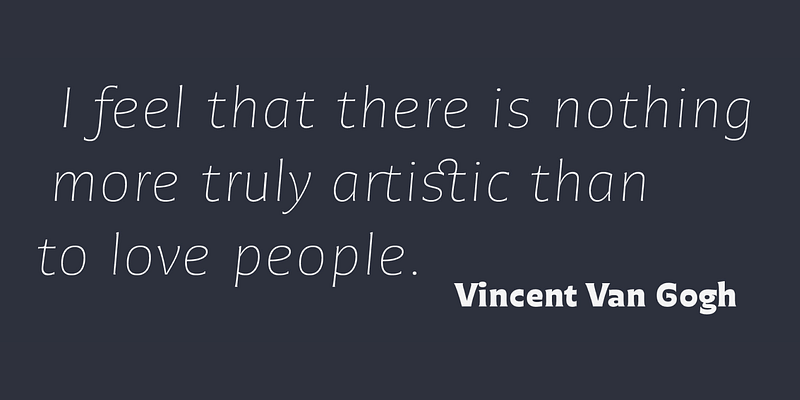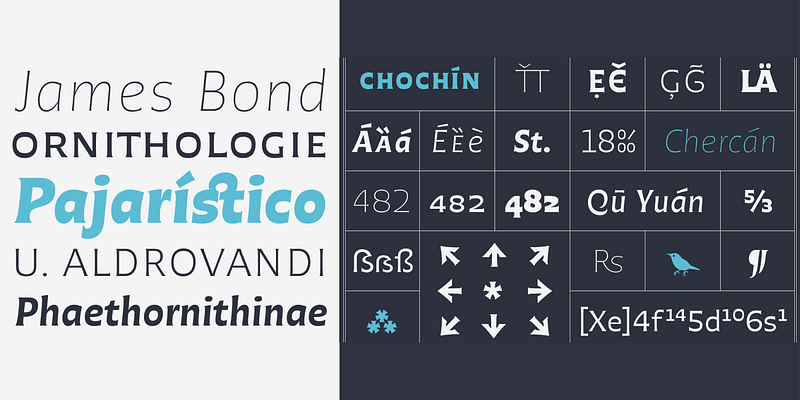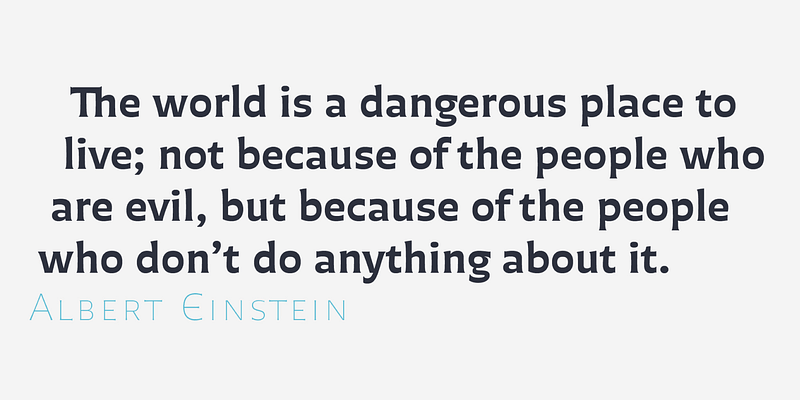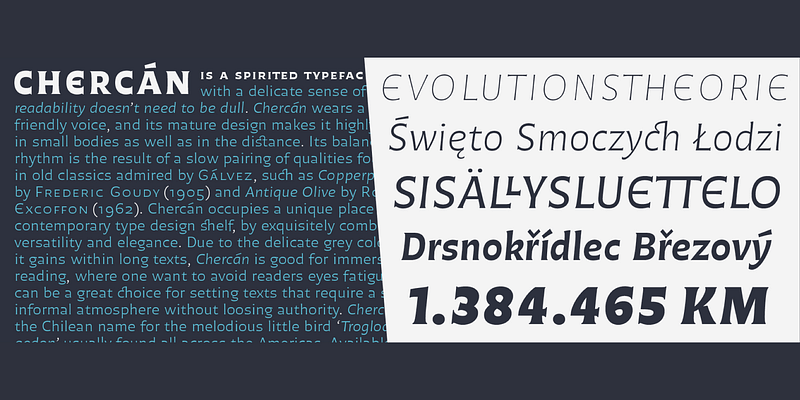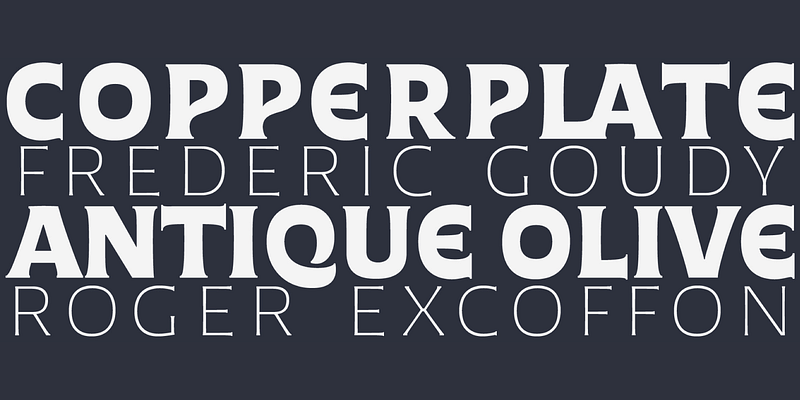
Chercán est une police de caractères élégante, très lisible et décontractée, ce qui en fait un bon choix pour les paramètres informels. Chercán a été conçu pour la lecture immersive, avec des lettres fortes et ouvertes et des formes de comptoir généreuses. Il communique la certitude avec un ton subtilement charmant. Ses petits empattements aident à construire une expérience de lecture agréable, certainement par rapport à celui d’un sans serif. Chercán a une personnalité positive, et ses caprices peuvent ajouter de l’épicerie aux titres, aux logos, aux emballages et aux gros corps en général. En 2021, une version grecque polytonique complète a été ajoutée à l’extension latine d’origine.